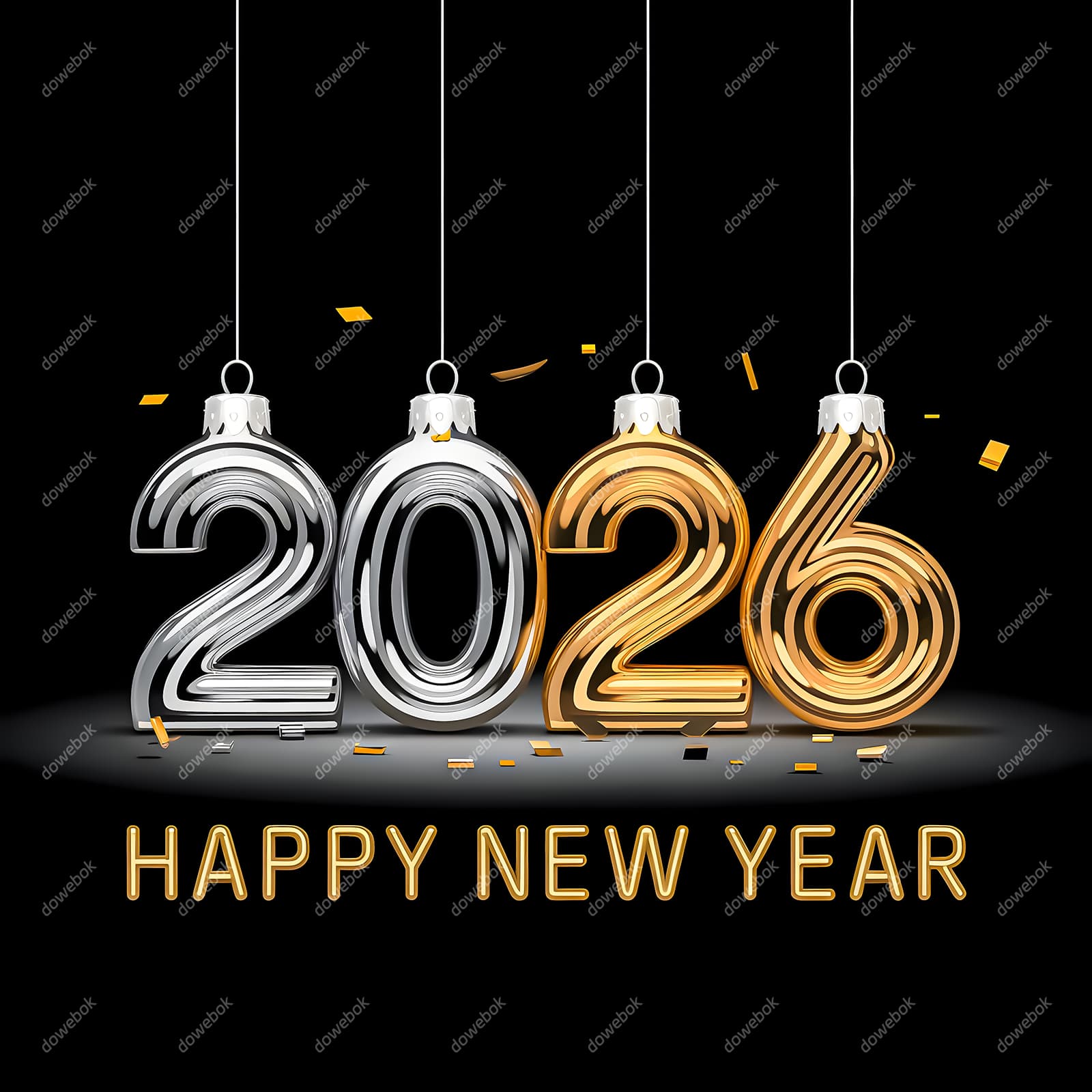
这是一款数字吊坠设计 2026 新年快乐素材,深黑背景下,“2026” 化作银、金双色装饰球,以挂绳悬垂,金属质感亮眼精致。周围散落的金箔碎片添了灵动氛围,下方衬着简约的 “Happy New Year”。整体以轻奢挂饰元素 + 金属光泽,既显跨年的雅致仪式感,又用金银配色透出温馨华丽的节日质感,精致又鲜活。